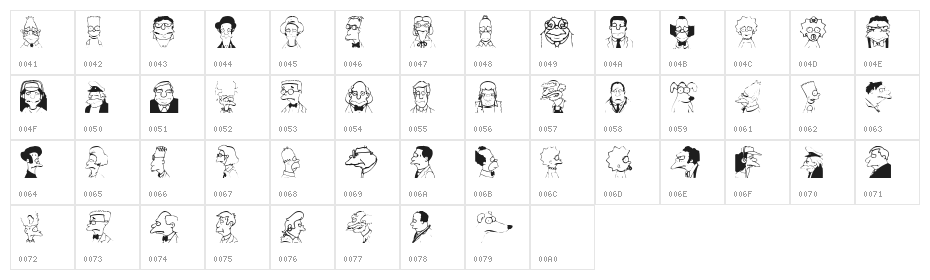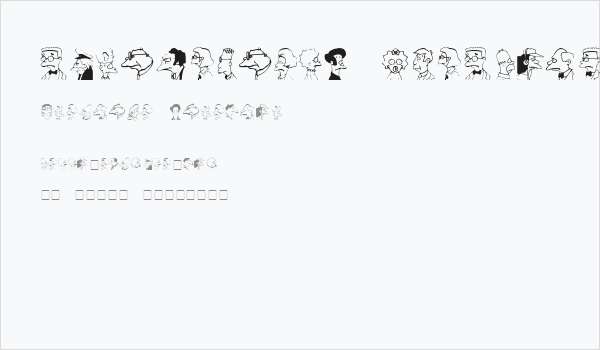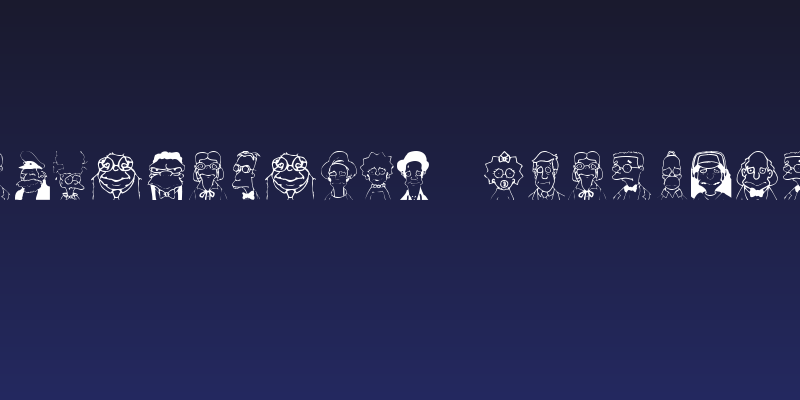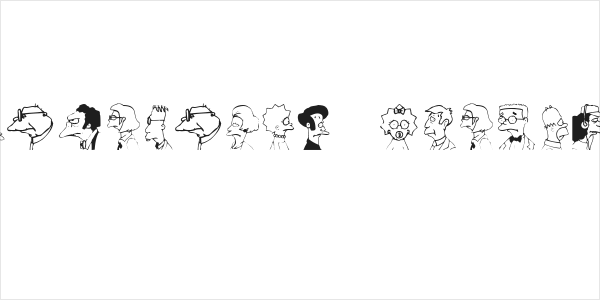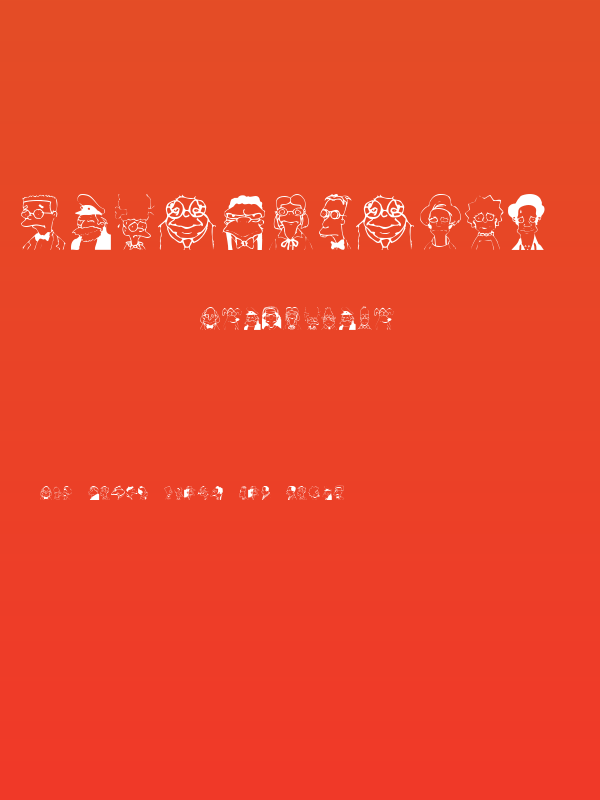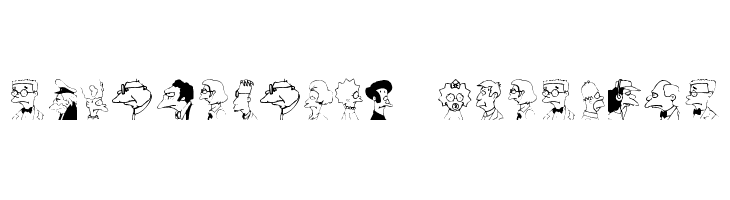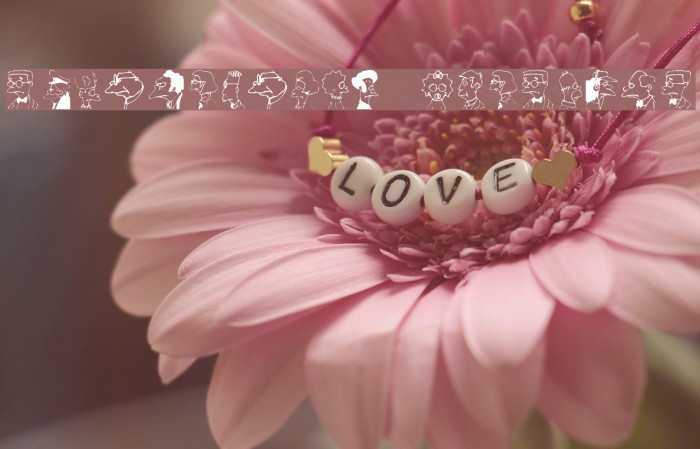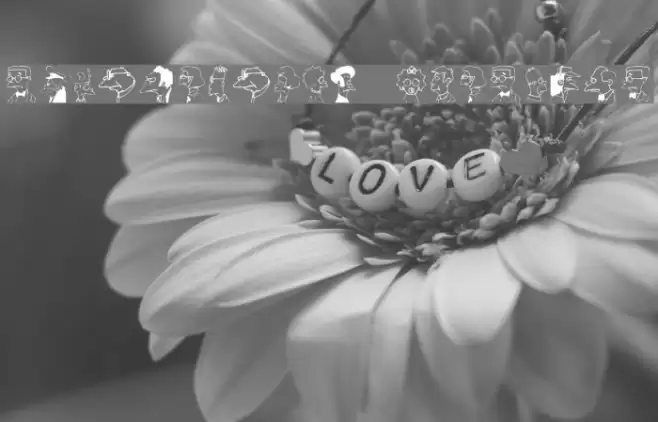
Springfield MugShots Font
| Gesamtstil | Decorative, Playful, Cartoonish |
| Anwendungsfall | Headlines, Logos, Posters, Themed Graphics |
| Vorgeschlagene Projekte | Posters, novelty invitations, themed party materials, comic book titles, children's event branding. |